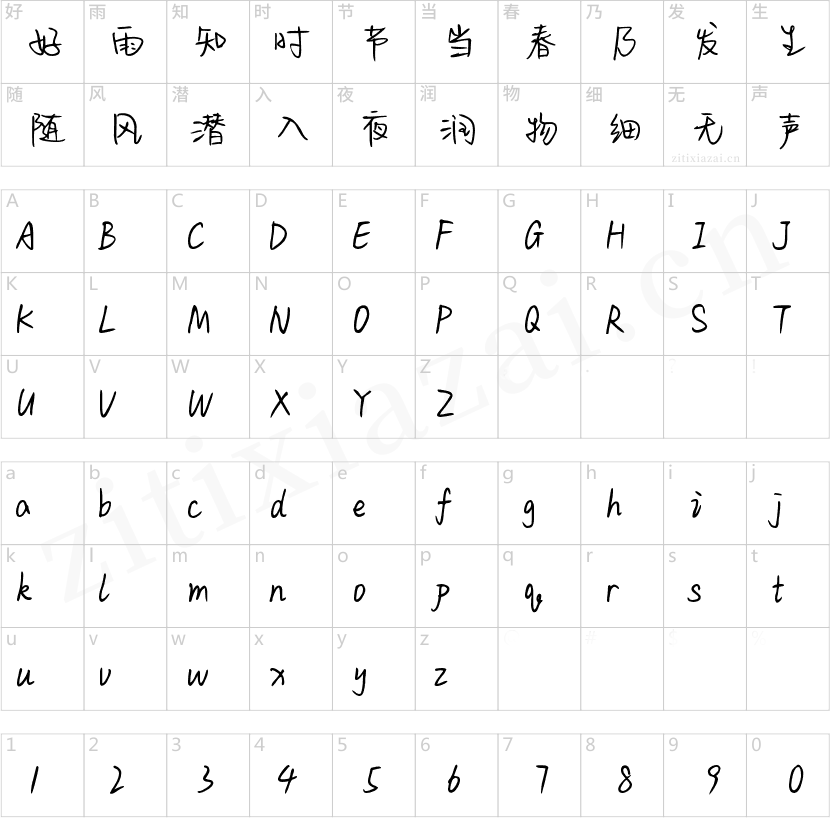
Aa初恋往事
Aa初恋往事,这款字体结构工整、笔画清晰,兼顾美观与易读性,适用于标题、正文、海报、包装、LOGO 等多种场景。字形优雅稳定,风格百搭耐看,适配日常排版与创意设计,让文字呈现更舒适、更具质感。Aa初恋往事一笔一画,皆是细节,以均衡的比例、流畅的线条打造舒适视觉体验,字形端正大气,风格简约现代。无论是商业设计、品牌宣传还是日常排版,都能轻松驾驭,让文字更有格调与力量。Aa初恋往事字体下载。
Aa初恋往事是一款非常具有艺术性的字体,它的设计灵感来源于对古典艺术的研究,同时又融入了现代字体设计的元素。字形优美,笔画粗细变化自然,给人以大气、典雅的感觉。Aa初恋往事是一款既传统又现代的字体,它的设计充满艺术感,美观大方,实用性也非常强。无论是对于设计师还是对于普通读者来说,都是一种非常不错的字体选择。Aa初恋往事适合用于具有艺术感的场合,比如海报、宣传单张、书籍封面等。由于其字形流畅且具有动态感,也适合用于大量的文本排版,如报纸、杂志等。